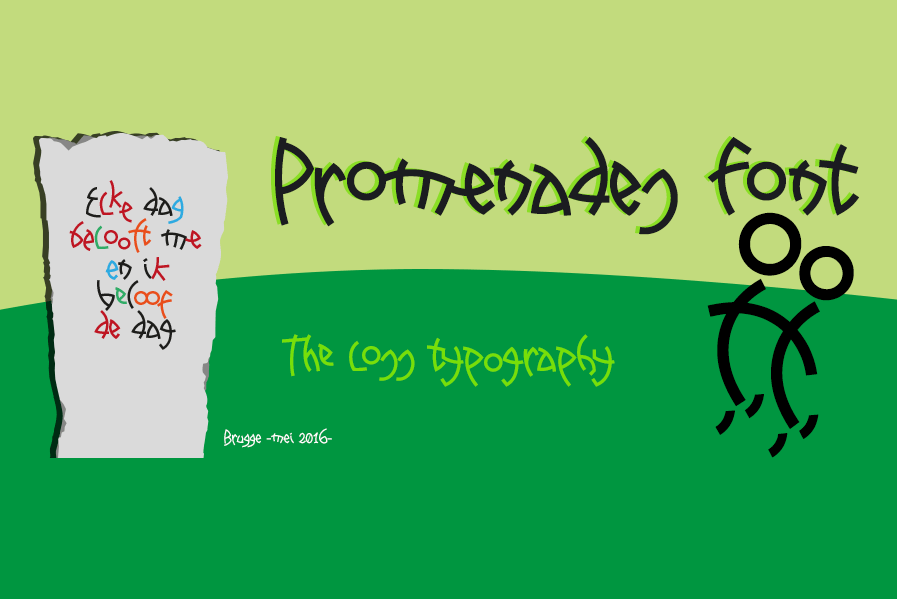
Promenades é uma nova adição à coleção das fontes script da Hamilton, desenvolvida a partir de uma impressão antiga encontrada durante uma caminhada pela bela cidade de Bruges no final do ano de 2016. O design é inspirado em um texto incrustado em pedra que prometia sempre cumprir suas promessas (Elke dag belooft me ik beloof dag), algo interessante e atraente à medida que era transformado para digitalização, resultando em uma tipografia moderna e relaxada. Este projeto ilustra como as antigas expressões escritas podem ser revitalizadas através da tipografia, oferecendo um toque de elegância moderna para uso em diversos ambientes gráficos. Promenades é a escolha perfeita para aqueles que desejam incorporar uma mistura românica e contemporânea em seus projetos visuais, tornando-a uma fonte versátil para textos como apresentações de PowerPoint ou designs da web.